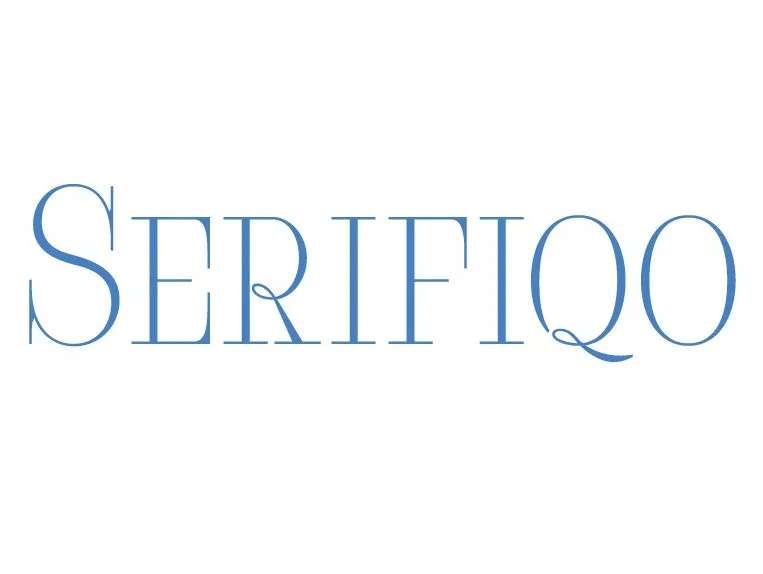
Serifiqo 4F é uma elegante fonte serif moderna que se destaca por seu design único e versátil. Ideal tanto para textos quanto para estilos visuais mais elaborados, esta fonte cativante encaixa-se perfeitamente em diversas aplicações gráficas. Suas características únicas tornam-na uma escolha ótima para criações de marca luxuosa ou sofisticadas, desde editoriais femininos e marcas cosméticas até galerias artísticas, museus e eventos especiais. Além disso, seu formato também se ajusta perfeitamente a designs de blogs, cartões de convite, ilustrações de citação, decorações domésticas e capas de livros, oferecendo uma variedade incrível de possibilidades criativas para designers. Com Serifiqo 4F, você pode explorar novos mundos de design sem limites.